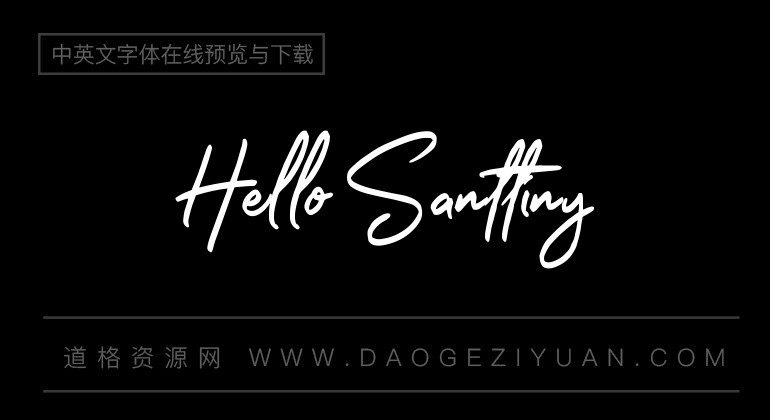
Hello Santtiny
Hello Santtiny 是一款经典的英文线条字体,由著名设计师Santiago Orozco所设计。它具有简洁、现代、时尚的特点,最大的特点就是它的线条细腻,给人一种精致的感觉。它有着完整的字母、数字、标点符号和特殊字符,可以用于各种印刷品的设计,也可以用于网页设计和社交媒体上的文字设计。
Hello Santtiny是一款非常不错的手写艺术字体,具有很好的视觉感,适合于文化类的宣传设计、商业类品牌的广告和产品包装设计以及个性化文字排版等较多场景。
Hello Santtiny字符映射图